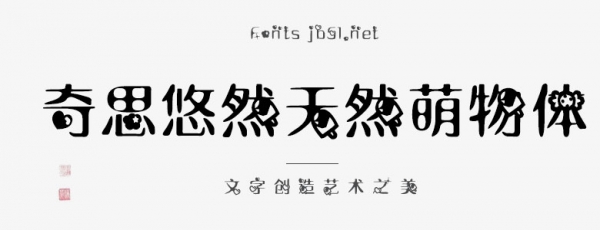
奇思悠然天然萌物體是一款不錯的藝術(shù)字體,由Aa字庫出品,字體筆觸適中,以心形、花朵以及糖果等卡通圖案作為點綴,具有很好的視覺感,適合應(yīng)用于藝術(shù)設(shè)計、平面宣傳設(shè)計、網(wǎng)頁設(shè)計,書法字帖等領(lǐng)域,需要的朋友可以前來本站下載。